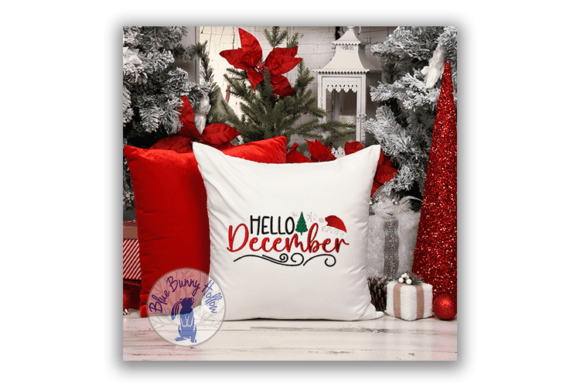
December
適切なデザイン要素を見つけるのは難しい場合がありますが、Decemberは作品を即座に引き立てる優れたコレクションを提供します。
精密に作られたDecemberは、クリーンなベクター、滑らかなタイポグラフィ、そして安心のための商用ライセンスを提供します。
POD(オンデマンド印刷)製品、結婚式の招待状、またはソーシャルメディアのグラフィックを作成している場合でも、Decemberは理想的です。